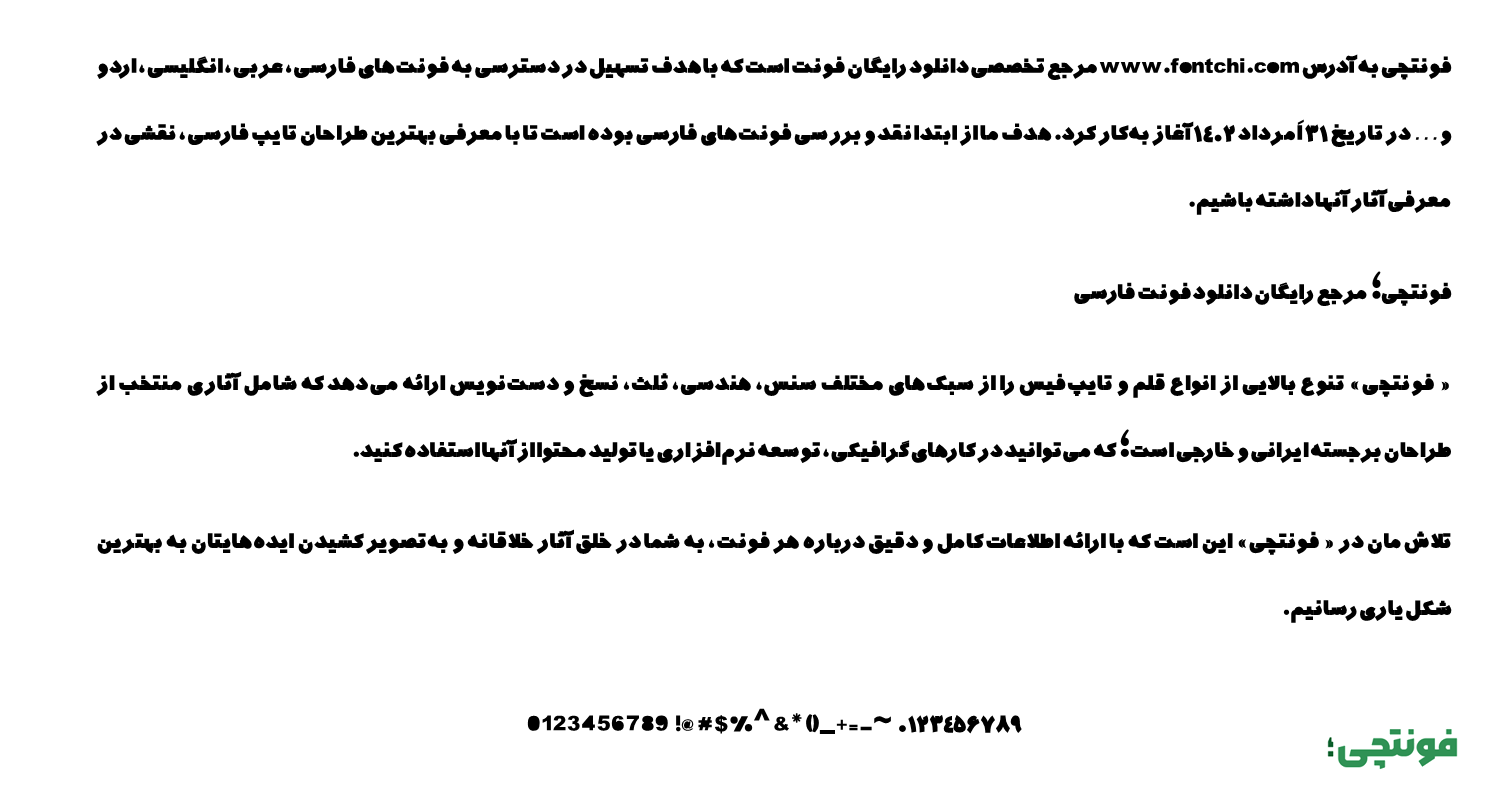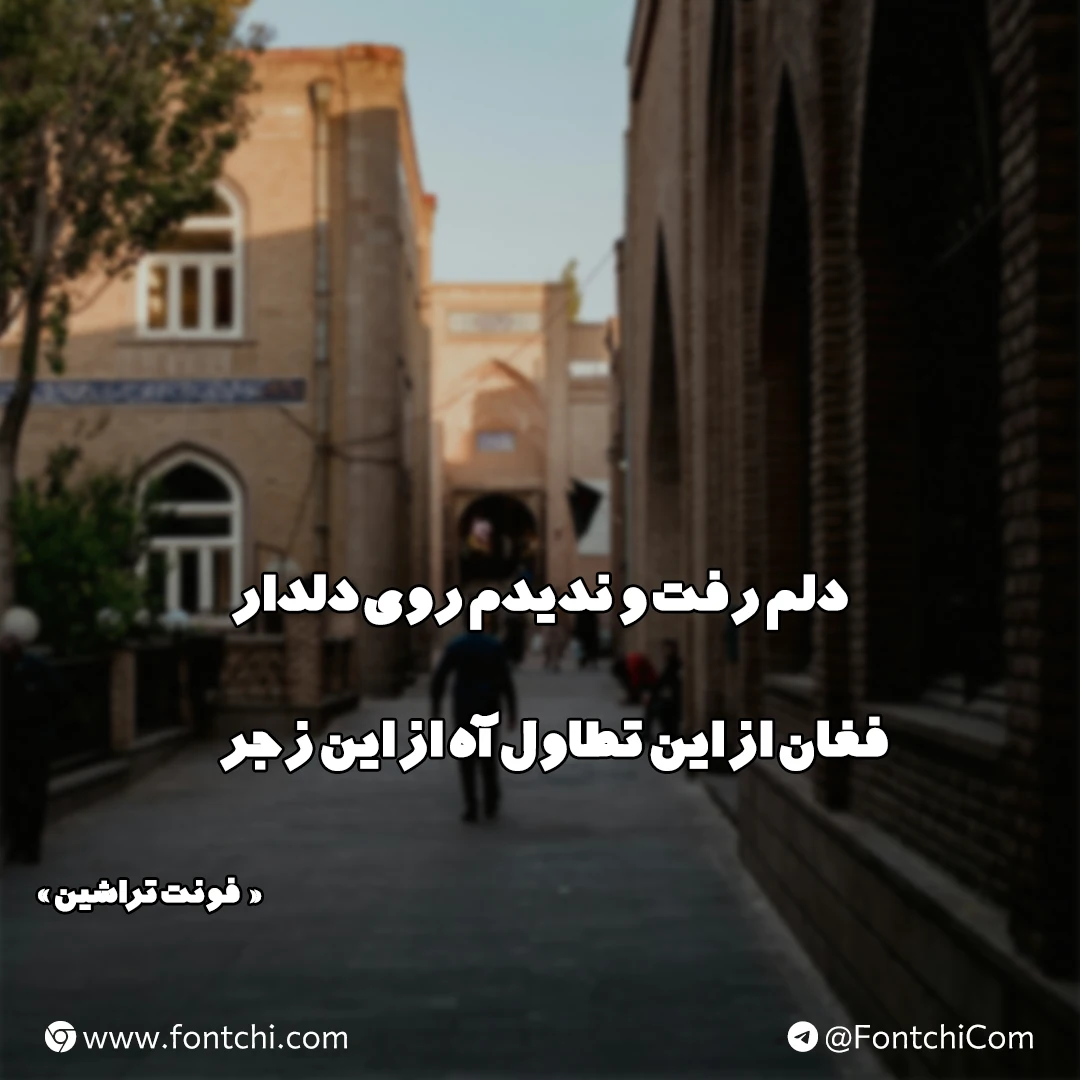
فونت تراشین (Trashin)
فونت تراشین (به انگلیسی: Trashin) از فونتهای فارسی مدرن شاهین صباغ است که بر پایه فونت معروف ترافیک (طراحیشده توسط مصطفی اوجی) توسعه یافته است.
این فونت فارسی با ویژگیهای منحصربهفردش توانسته جایگاه خوبی در میان طراحان گرافیک، تایپوگرافها و تولیدکنندگان محتوا پیدا کند. تراشین با ظاهری سنس سریف (Sans Serif)، ساختاری جسور و نمایشی ارائه میدهد که آن را برای استفاده در عناوین، پوسترها و طراحیهای گرافیکی جذاب میسازد. در ادامه، به بررسی ویژگیها، نقاط قوت و ضعف این فونت میپردازیم.
معرفی و دانلود فونت تراشین رایگان (Trashin)
فونت تراشین با الهام از فونت ترافیک، نسخهای ضخیمتر و جسورتر از آن ارائه میدهد. این فونت با ظاهری سنس سریف، خطوطی تمیز و هندسی دارد که حس مدرنیته و قدرت را منتقل میکند. وزن بولد آن باعث شده که برای تیترها و متنهای برجسته بسیار مناسب باشد.
برخلاف فونتهای سنتی یا خوشنویسی، تراشین ساختاری منطقی و خوانا دارد که حتی در اندازههای بزرگ نیز کیفیت خود را حفظ میکند. این ویژگی آن را به گزینهای ایدهآل برای طراحیهای گرافیکی مدرن، مانند کاورهای اینستاگرام، بنرهای تبلیغاتی و لوگوتایپ تبدیل کرده است.
تراشین از سه زبان فارسی، عربی و انگلیسی پشتیبانی میکند. در زبان فارسی، اعداد بهغیر از «۴۵۶» بهشکل استاندارد تایپ میشوند. در زبان عربی، اعرابگذاری دقیق و گلیفهای مرتبط بهخوبی پیادهسازی شده و در همنشینی با سایر اعراب و گلیفهای تزئینی بهخوبی ظاهر خود را حفظ میکنند.
در مقایسه با فونتهای سنس سریف دیگر مانند ایران سنس یا وزیرمتن، تراشین ظاهری غیررسمیتر و نمایشیتر دارد. ایران سنس با وزنهای متنوع و خوانایی بالا برای متون طولانی مناسبتر است، در حالی که تراشین برای تیترها و طراحیهای گرافیکی برتری دارد.